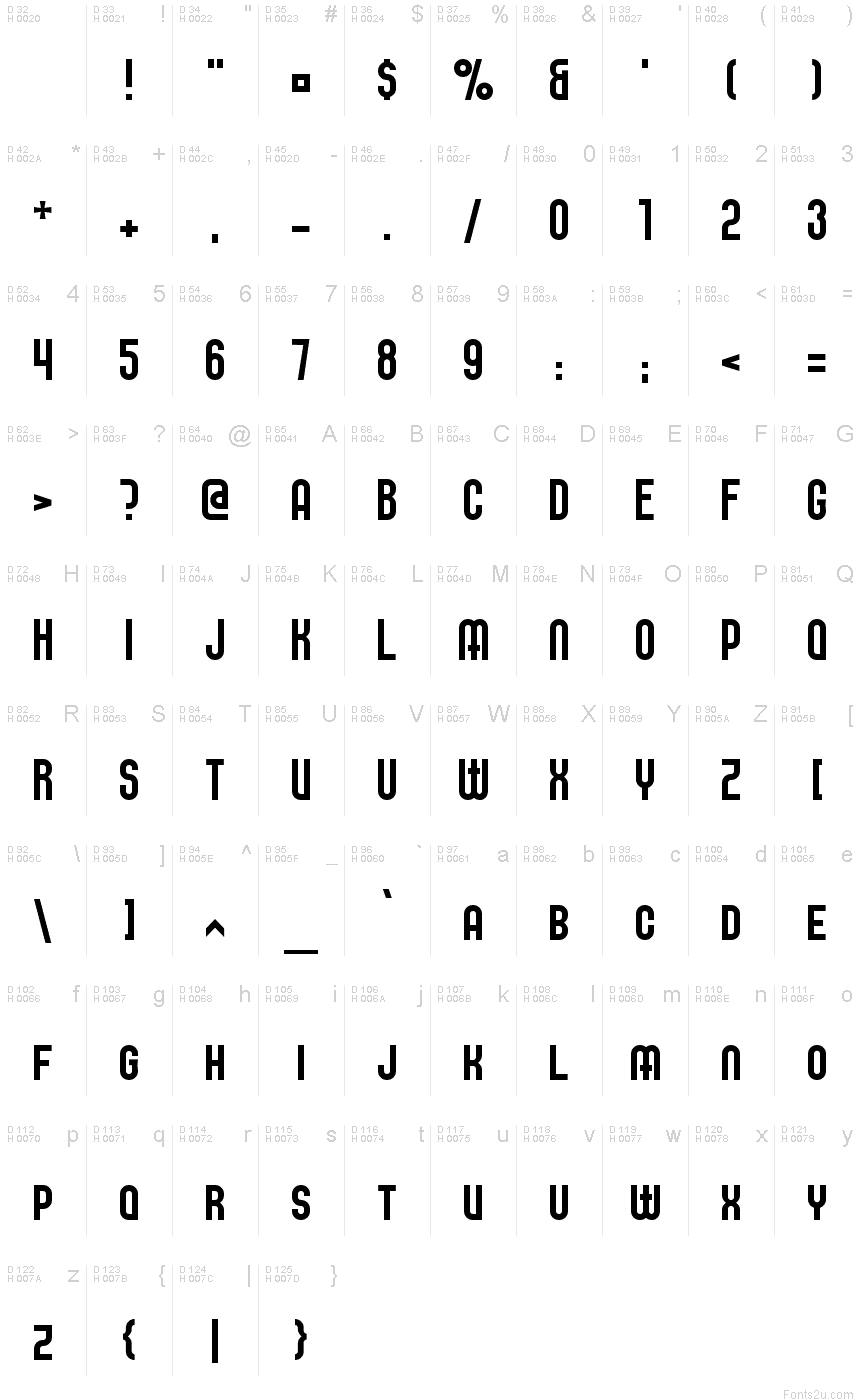
Elbaris, die kostenlose serifenlose Schrift von Peter Wiegel, besitzt die direkte, plakative Ausdrucksstärke kondensierter industrieller Beschriftungen. Die Großbuchstaben wirken hoch und eng gesetzt, mit rechtwinkligen Ecken, tiefen Einschnitten und einem stoischen Rhythmus, der der Schrift eine sachliche, urbane Ästhetik verleiht.
Sie passt perfekt auf Plakate, Plattencover, Buchtitel, Titelkarten und für markantes Branding, bei dem es auf eine schmale, gewichtige Typografie ohne Schnörkel ankommt. Als Freefont eignet sich Elbaris hervorragend für Cover-Texte, Monogramme und knackige Überschriften, da die Buchstaben zu einem kompakten, entschlossenen und kantigen Block verschmelzen.